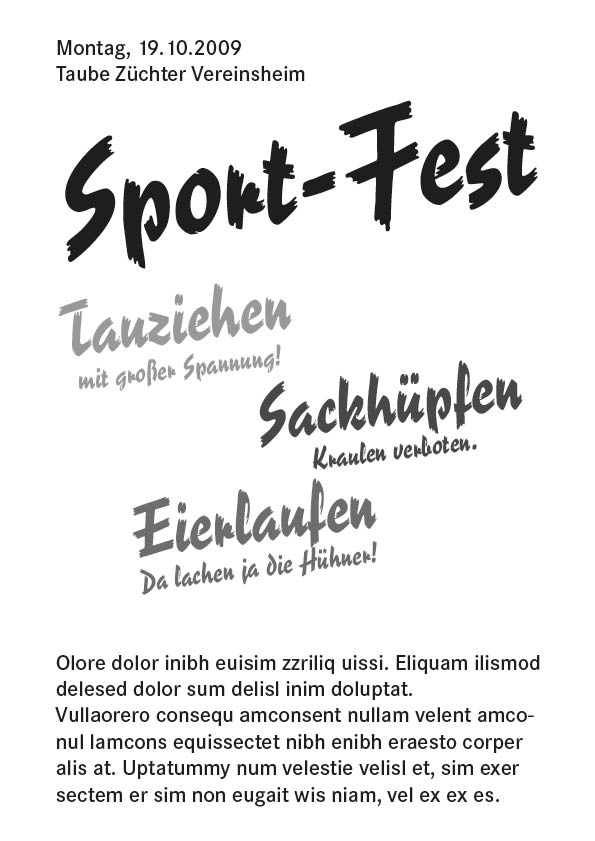
Input für Schriftwahl "Sportfest"
steh grad auf dem Schlauch: Soll ein Plakat (und Einladung) für eine schulische Veranstaltung gestalten und such nach was passendem für die Headlines.
Stichworte: Sportfest Schule Fröhlichkeit
Da geht natürlich im Prinzip ganz viel und ich will da auch keine Wissenschaft draus machen, aber wenn ihr ein paar eurer Spontanst-Ideen preisgeben würdet, wär mir beim "Einkreisen" irre geholfen und ich könnt mal systematischer in meinem Schriftenfundus stöbern; mir ist jetzt nämlich beim wahllosen Rumtesten die Orientierung bissi verloren gegangen ...
Comic Sans
... wenn ich nicht genau wüsste, dass du min. 10 bessere Ideen hast ... so isses halt eine Art Meta-Running-Gag ...
Schulsportfest und Fröhlichkeit sind ja solch conträre Begriffe, daß ich mir kaum vorstellen kann, was für eine Schrift sowohl das eine wie auch das andere abdecken soll. :?
Vor Jahren hätt ich das noch als Running Gag beschmunzelt.
Also ich weiß nicht, was du für eine Erinnerung an Schule hast, bei uns ist's oft fröhlich... ;-), echt!
Aber ich war auch unklar: Es geht um das traditionelle Schulfest, das alljährlich im Herbst, sprich jetzt in 3 Wochen stattfindet und das heuer ein sportliches Motto bekommt: "Olympische Herbstspiele" oder so. Da veranstalten die Klassen allerlei Gaudiwettkämpfe für die Gäste und mit den Gästen, es gibt Turn- und Tanzvorführungen, keine verbissenen Kämpfe um den ersten Platz.
… traditionelles Schulfest … sportliches Motto … "Olympische Herbstspiele" …
das ist doch schon mal was. Wenn es "nur" für die Headline sein soll, dann greif doch den Gedanken "Olympische Spiele" auf und gestalte es beispielsweise griechisch oder verwende ein China-Derivat …
das ist doch die aufgabe der gestaltung nicht der schrift, da geht wirklich viel, man könnte es mit clarendon machen aber auch mit der sauna oder sogar was selbst gezeichnetes wie das hier.
Jo, danke, seh schon etwas klarer:
Typografski hat natürlich völlig recht, nur bekomm ich eine Gestaltung wie in seinem Beispiel auf die Schnelle nicht hin, hab das leider nicht gelernt. Die Plakate von der rwth Aachen sind aber schon mal eine gute Inspiration in die Richtung "mit rel. neutraler Serifenlosen dynamisch gestalten".
Griechischer Einschlag in der Typo: prima Idee, werd' ich mal kurz mit den Verantwortlichen ventilieren, Chinesische Anmutung war auch mein erster Gedanke, lass ich aber sicher davon ab, Peking hat mir politisch zu stark polarisiert.
Idee grad beim Autofahren: Zur WM '96 war die Trivia aktuell: meint ihr, die Assoziation zu "Sport, Sommermärchen, ganz-Deutschland-ungewohnt-ausgelassen" funktioniert bei Nicht-Typografen noch nach zwei Jahren?
Wenn ihr mir nimmer anderweitig die Augen öffnet, will heut abend einen Vorschlag basteln:
Trivia oder Lithos ( :rockon: muhaha, ganz innovativ ...)
Vielleicht sowas?
so? Reporter und Corporate S sind auch nicht schlecht… :cheer:
Nochmal "Danke". Neuropol läuft in meinen Augen auf der Trivia-Schiene, nicht schlecht, bekäm ich wohl mehr Schnitte. Reporter ist "no go" Wir innovieren die Schule bis zur Atemnot und erinnern uns beim Feiern an die 50er? Oder derb ironisch ("Sackhüpfen und Eierlaufen, Kraulen verboten")? Man, eure Schulzeit muss lang her sein, ich sach nur "Schulsportfest und Fröhlichkeit" ...
… derb ironisch? …
derb ironisch. Ich mach das immer ohne den Ironie-Smiley.
… Reporter ist "no go" Wir innovieren die Schule bis zur Atemnot …
Gerade dann kann doch ein "Retro-Fest" ein interessantes Motto sein. Ich kenn aber eure Planungen nicht.
... auch wieder wahr, aber das will halt auch verstanden werden. Ein Spiel mit dem Feuer, wenn man das einfach so plakatiert und 800 Mamas und Papas am Küchentisch die Deutungshoheit haben, ohne das man steuernd und interpretierend eingreifen kann ...